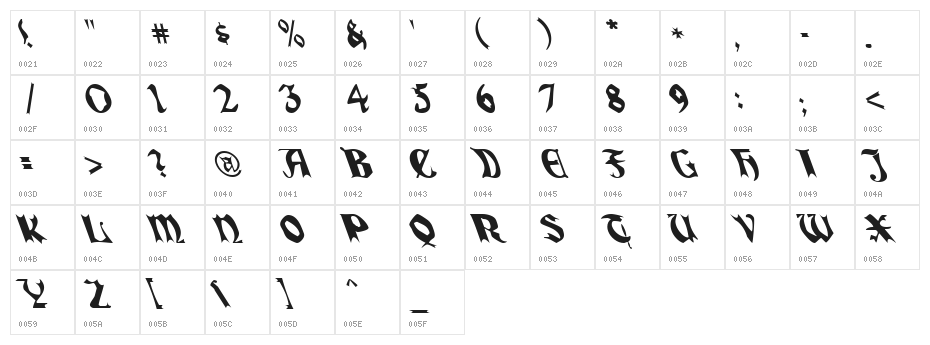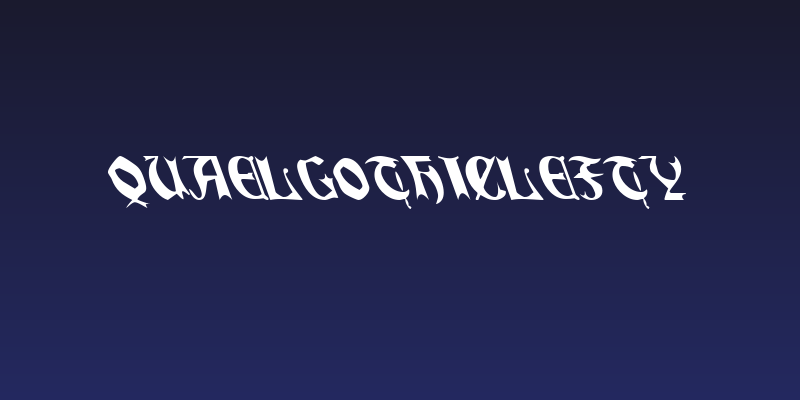
QuaelGothicLefty Font
Questo font include 101 caratteri. Clicca su un carattere per vedere i dettagli.
| Stile generale | Gothic, Decorative |
| Progetti proposti | Ideal for use in album covers, posters, branding for edgy or alternative products, and any design requiring a bold statement. |